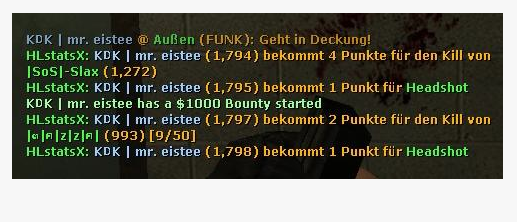
Suche Schrift(en) aus dem Spiel Counterstrike Source
Ich habe nach einiger Zeit googeln immer noch eine Frage offen. Und zwar wie heißt die Schrift, die in dem Spiel Counterstrike Source bei den Einblendetexten unten links und auch für alle anderen Texte und Wörter, die ingame zu sehen sind, verwendet wird? Ich habe eine Beispielgrafik angefügt.
Desweiteren würde mich die genaue Bezeihnung der verwendeten Schrift aus der Konsole interessieren. Sie ist nicht besonders, und kommt mir auch sehr bekannt vor.
Was die Grafik anbelangt, habe ich auch nur eine angehängt und das ist die, der Schrift, die ingame zu sehen ist. Ich hoffe mir kann jemand sagen, welche Schrift das ist, die auf der von mir angehängten Grafik zu sehen ist.
Ähm, wo ist denn da noch eine Schrift? Ich sehe nur ein recht dunkles Hintergrundbild ohne Schrift auf dem ein bunter Dialog in der oben erwähnten Schift plaziert ist.
Früher wurde die Schrift auch beim mIRC-Programm verwenden. Mir ist aber leider entfallen, welche das ist.
Die Schrift, die ich suche ist Verdana. Das ist die, die auf dem von mir im ersten Post gezeigten Bild zu sehen ist. Zur Schrift der Konsole habe ich kein Beispiel zur Veranschaulichung angehängt. Diese Schrift habe ich aber inzwischen selber harausgefunden. Danke!
Ich hatte mir besagte Schrift auch schon näher angeschaut, da diese im Spiel eher klein zu sehen ist (Beispielgrafik ist ein Ausschnitt in Orginalgröße). Und bin leider nicht gleich auf die richtige Schrift gekommen, denn die Schrift hat durchgehend eine Darstellung mit Schatten etc.